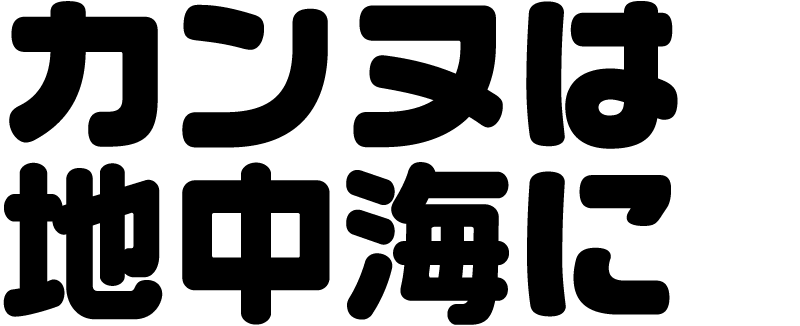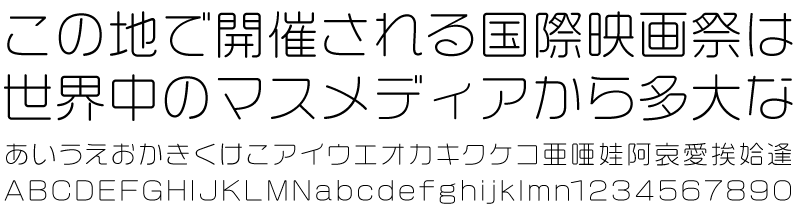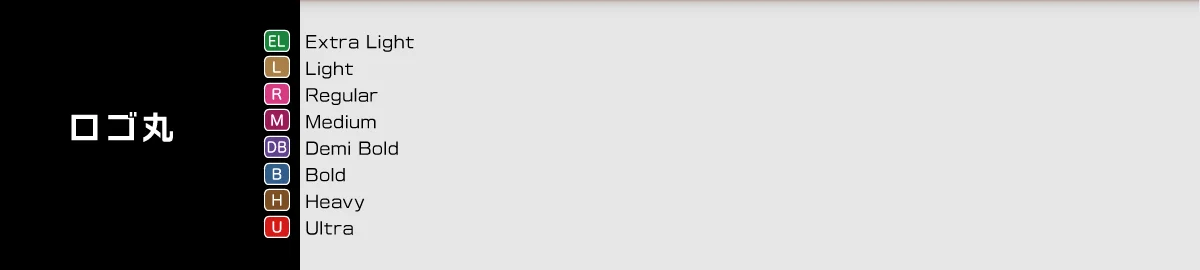
ロゴ丸の特徴
文字組がピタッと揃う「ロゴG」をベースに生まれた、バランスのよい丸ゴシック体です。おおらかな曲線、広いふところに加えて、始筆・終筆部を丸く処理することで、ソフトで親しみやすい表情を生み出しました。
ロゴ丸の特徴
文字組がピタッと揃う「ロゴG」をベースに生まれた、バランスのよい丸ゴシック体です。おおらかな曲線、広いふところに加えて、始筆・終筆部を丸く処理することで、ソフトで親しみやすい表情を生み出しました。
ロゴ丸-EL
ロゴ丸-L
ロゴ丸-R
ロゴ丸-M
ロゴ丸-DB
ロゴ丸-B
ロゴ丸-H
ロゴ丸-U